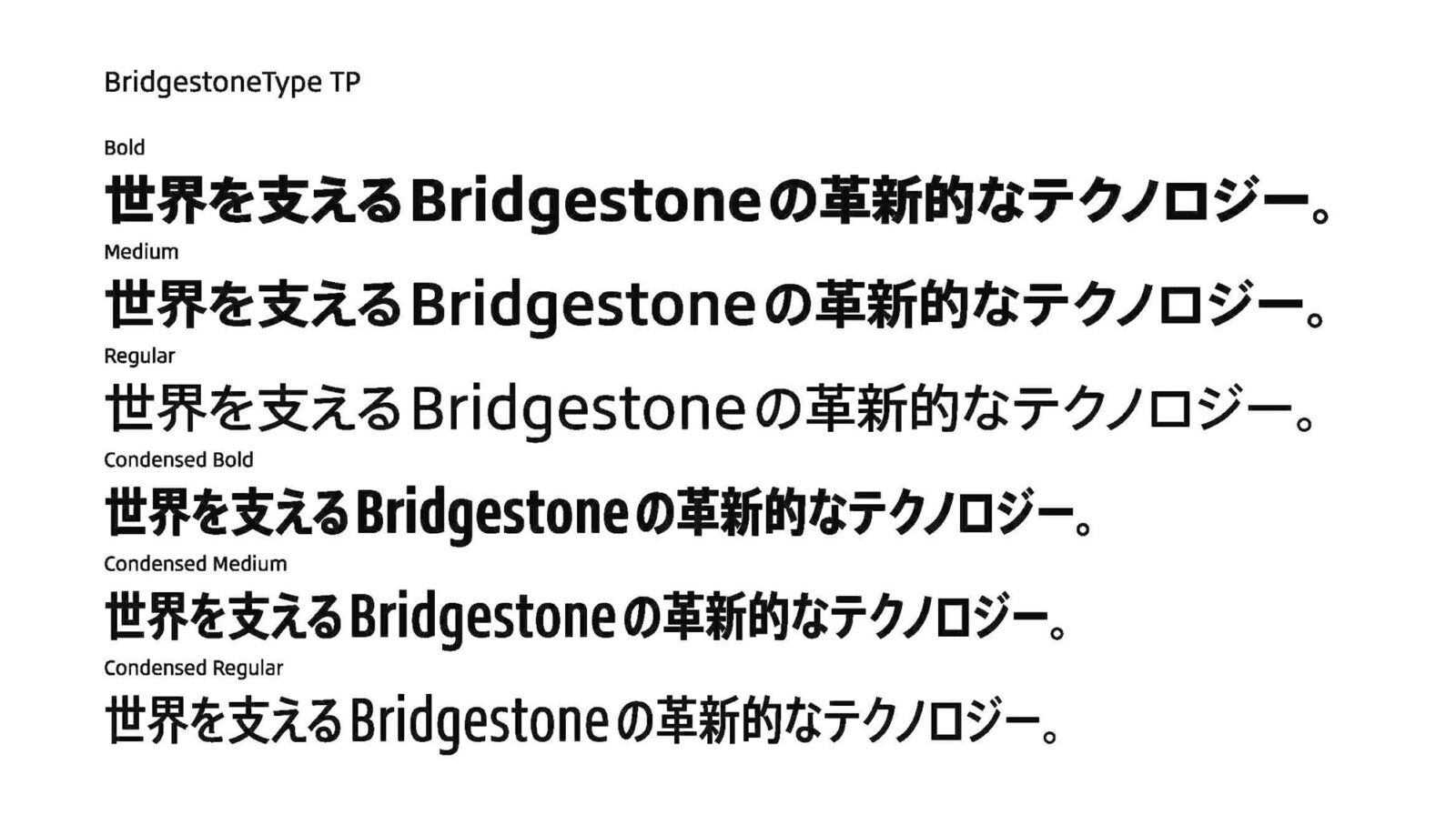
タイププロジェクト、ブリヂストンに和文コーポレートフォント 「BridgestoneType TP」を提供
タイププロジェクト株式会社(東京都練馬区 代表取締役社長 鈴木 功、以下タイププロジェクト)は、本日、株式会社ブリヂストンがMonotypeの協力のもと開発した欧文コーポレートフォントに合わせて調整した AXISフィットフォントを「BridgestoneType TP」として提供したことを発表しました。
「コーポレートフォントの導入の主目的は、社外に対して統一感のあるブリヂストンらしさ、ブランドイメージを表現することにありますが、ブリヂストングループ従業員にも日常業務で使用してもらうことでブランドに対する意識向上、一体感、プライドの醸成といったインターナルブランディング面での効果も意図しています。」と株式会社ブリヂストン コーポレートブランド部門 BRIDGESTONE DESIGN部 上席研究主幹の酒本康平氏は述べています。
コーポレートフォントのグローバル展開を進める中で、日本でのブランド表現のためにサインにも本文にも対応できる汎用性の高さ、コンデンス体を持っている点など和文書体の条件を最も満たす書体としてAXIS Fontが選ばれました。
コーポレートブランド部門 ブランド管理課の森田明伸氏は、「最終的にはデザイン面での親和性に加え、Webフォントを含む運用面や導入コストなどの点から総合的に判断した結果、AXIS Fontが最適であるとの結論となり採用に至りました。」と述べています。
タイププロジェクトは、欧文コーポレートフォントに合わせてAXIS Fontのウエイトや字幅を設定し、さらに欧文書体の拡大率とベースラインを調整して「BridgestoneType TP」として提供しました。ウエイトや字幅の調整には、自社開発したフィットフォント技術を用いています。
BridgestoneType TPは名刺、封筒などのコーポレートアイテム、施設サイン、広報、広告宣伝、イベント、販促ツール、Webサイト等、さまざまな社外コミュニケーションでの使用が想定されています。
タイププロジェクトでは、企業のメッセージを伝えるための手段としてフォントによるブランディングを提案しています。フィットフォント技術を用いて、AXIS FontやTP明朝、TPスカイのウエイトや字幅、コントラスト、フトコロ軸を調節することで最適な組合せを提供します。欧文部を他社欧文と組替えるほか、オリジナルのひらがなやカタカナを開発するなど、世界有数のグローバル企業にコーポレートフォントを提供しています。